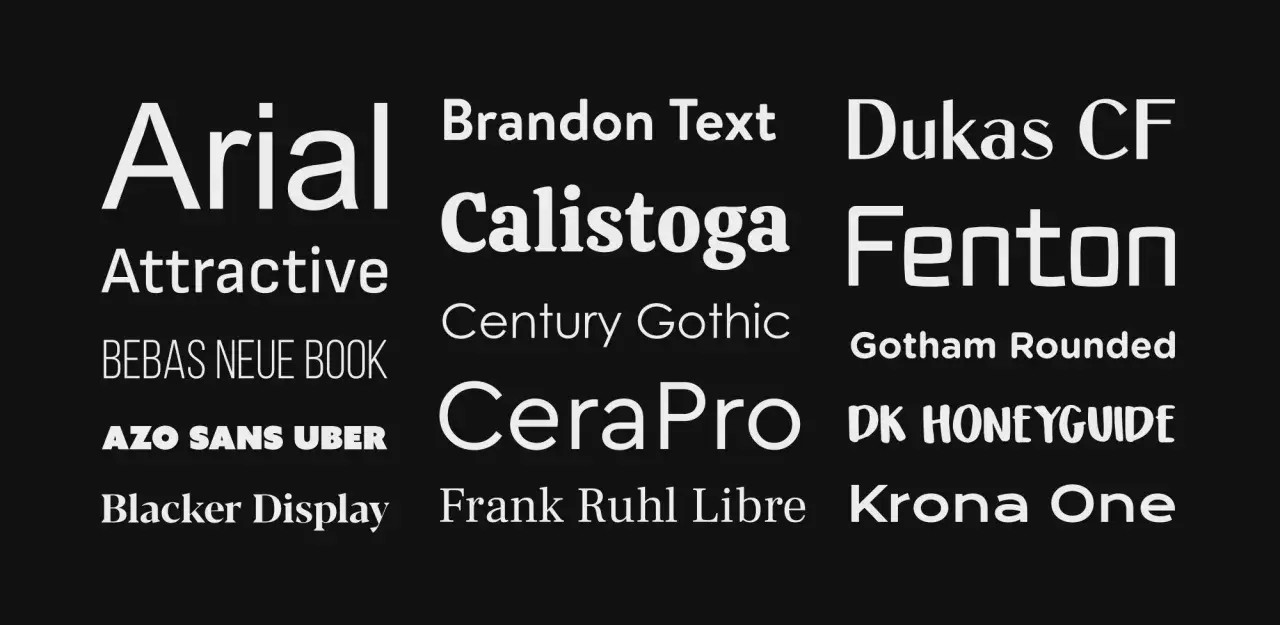
Czy krój liter w logo, plakacie albo książce to po prostu font? To zależy od tego, czy mówimy o wyglądzie znaków, czy o cyfrowym pliku, który pozwala ten wygląd wyświetlić i wydrukować. Wyjaśniam definicję fontu, różnicę między fontem, krojem pisma i czcionką, a także pokazuję, jak dobierać oraz poprawnie stosować fonty w projektach wizualnych.
Font łączy projekt liter z ich cyfrowym zastosowaniem
- Font to cyfrowy zapis zestawu znaków używany przez komputer, telefon lub program graficzny.
- Krój pisma opisuje wygląd liter, a font jest jego cyfrową realizacją.
- Czcionka w tradycyjnym znaczeniu była fizycznym elementem drukarskim, choć dziś słowo to bywa używane potocznie.
- Dobry wybór zależy przede wszystkim od czytelności, przeznaczenia i języka projektu.
Co dokładnie oznacza font
Najprościej mówiąc, font to cyfrowy zestaw znaków zapisany w formie, którą potrafi odczytać system operacyjny lub program. Zawiera nie tylko litery, lecz także cyfry, znaki interpunkcyjne, symbole i informacje potrzebne do prawidłowego rozmieszczenia ich w tekście.
Gdy instaluję font na komputerze, nie dodaję do systemu pojedynczego obrazka z alfabetem. Dodaję dane opisujące kształt znaków, ich proporcje, odstępy oraz sposób wyświetlania w różnych rozmiarach. Dzięki temu ten sam zapis może pojawić się na stronie internetowej, w katalogu, na plakacie albo w publikacji drukowanej.
W codziennej rozmowie słowo „font” często oznacza po prostu wygląd pisma. Technicznie precyzyjniej jest jednak powiedzieć, że font jest cyfrową realizacją określonego kroju pisma. To rozróżnienie nie zawsze ma znaczenie przy pracy w edytorze tekstu, ale przy projektowaniu, licencjonowaniu i przygotowaniu materiałów do druku staje się bardzo praktyczne.
Font, krój pisma i czcionka to nie to samo
Te trzy pojęcia są często mieszane, ponieważ w programach graficznych i rozmowach projektowych funkcjonują niemal zamiennie. Ja rozdzielam je w prosty sposób, patrząc na to, co jest projektem, co zapisem, a co fizycznym nośnikiem.
| Pojęcie | Znaczenie | Przykład |
|---|---|---|
| Krój pisma | Projekt i charakterystyczny wygląd całego zestawu znaków. | Helvetica, Garamond, Futura |
| Font | Cyfrowy zapis kroju pisma wraz z konkretnymi danymi i odmianami. | plik Garamond-Regular.otf |
| Czcionka | Tradycyjnie fizyczny element używany w składzie drukarskim. | metalowy klocek z literą |
Krój pisma można porównać do projektu mebla, a font do pliku technicznego, na podstawie którego ten mebel da się wykonać. Czcionka była natomiast konkretnym, materialnym elementem używanym przez drukarza. Współczesny język komputerowy spłaszczył te różnice, dlatego określenie „czcionka” jest dziś często potocznym odpowiednikiem słowa „font”.
Podobnie działa pojęcie rodziny fontów. Jedna rodzina może obejmować odmianę regularną, pogrubioną, kursywę, wersję półgrubą i wąską. Nie są to całkowicie przypadkowe warianty, lecz spójny system zaprojektowany do różnych funkcji, takich jak tekst główny, nagłówki czy wyróżnienia.
Jakie informacje zawiera cyfrowy font
Font przechowuje kształty znaków, nazywane glifami. Glif to konkretny graficzny wariant znaku, dlatego jedna litera może mieć kilka glifów, na przykład zwykłą formę, ozdobną alternatywę albo wersję używaną w ligaturze.
Znaki i obsługiwane języki
Przy polskich projektach szczególnie ważny jest zestaw znaków diakrytycznych. Font powinien zawierać między innymi ą, ć, ę, ł, ń, ó, ś, ź i ż. Brak tych znaków prowadzi do zastępowania ich innymi krojami, pustymi kwadratami albo literami bez ogonków, co natychmiast psuje spójność kompozycji.
Odstępy i układ tekstu
O jakości fontu decydują także dane dotyczące kerningu, czyli korekty odstępów między konkretnymi parami liter. Para „A” i „V” może wymagać innego ustawienia niż „H” i „I”. W krótkim napisie logo takie szczegóły są bardzo widoczne, choć w długim akapicie łatwo je przeoczyć.
Font może również zawierać informacje o wysokości liter, linii bazowej, interlinii oraz proporcjach znaków. To dlatego dwa fonty ustawione w tym samym rozmiarze, na przykład 12 punktów, mogą wyglądać na różnej wielkości i zajmować zupełnie inną ilość miejsca.
Format pliku
Do najczęściej spotykanych formatów należą TTF i OTF, wykorzystywane głównie w systemach operacyjnych oraz programach graficznych. W internecie stosuje się przede wszystkim WOFF i WOFF2, ponieważ zostały przygotowane z myślą o wydajnym ładowaniu fontów na stronach.
W starszych projektach można znaleźć format Type 1, ale nie powinien być pierwszym wyborem przy nowych realizacjach. Coraz większe znaczenie mają również fonty zmienne, które w jednym pliku mogą przechowywać płynne zakresy grubości, szerokości lub pochylenia. Dają projektantowi większą elastyczność, lecz nie każdy program i system obsługuje je w identyczny sposób.
Najważniejsze rodzaje fontów i ich zastosowanie
Podział fontów nie służy wyłącznie porządkowaniu katalogów. Każdy rodzaj niesie określone skojarzenia i inaczej zachowuje się w tekście. Przy wyborze zaczynam od funkcji projektu, a dopiero później zastanawiam się, czy dany krój jest modny albo efektowny.
Fonty szeryfowe
Fonty szeryfowe mają niewielkie zakończenia kresek, czyli szeryfy. Kojarzą się z tradycją, literaturą i drukiem, dlatego często dobrze sprawdzają się w książkach, esejach, albumach oraz tekstach o historycznym lub artystycznym charakterze.
Ich ozdobne zakończenia nie gwarantują automatycznie lepszej czytelności. Przy małym rozmiarze, słabym kontraście lub na ekranie o niskiej jakości mogą stać się zbyt drobne. Zwykle wybieram je tam, gdzie tekst ma mieć spokojny, bardziej redakcyjny charakter.
Fonty bezszeryfowe
Fonty bezszeryfowe, nazywane też groteskami, nie mają dodatkowych zakończeń kresek. Są prostsze wizualnie i często dobrze działają w interfejsach, podpisach, prezentacjach oraz materiałach przeznaczonych głównie do czytania na ekranie.
Nie oznacza to, że każdy bezszeryfowy font będzie dobry dla strony internetowej. Zbyt cienka odmiana może znikać na telefonie, a zbyt ciasne odstępy utrudnią czytanie. Liczy się konkretna konstrukcja znaków, nie sama etykieta kategorii.
Fonty odręczne i dekoracyjne
Fonty skryptowe naśladują pismo ręczne, kaligrafię lub lettering, a dekoracyjne mają silnie indywidualny charakter. Potrafią nadać plakatowi czy zaproszeniu wyjątkowy ton, jednak zwykle najlepiej używać ich w krótkich napisach, nie w wieloakapitowym tekście.
Najczęstszy błąd polega na stosowaniu ozdobnego fontu wszędzie, gdzie chcemy dodać projektowi charakteru. W praktyce wystarczy jeden wyraz lub nagłówek, a resztę dobrze oprzeć na spokojniejszym kroju. Dzięki temu akcent pozostaje czytelny i nie zamienia kompozycji w wizualny chaos.
Przeczytaj również: Ozdobniki tekstu w liternictwie - jak dekorować bez chaosu
Fonty monospacowane
W fontach monospacowanych każdy znak zajmuje taką samą szerokość. Kojarzą się z maszyną do pisania, kodem i estetyką techniczną, dlatego mogą pasować do plakatów inspirowanych komputerami, archiwami lub drukiem.
W zwykłym tekście zajmują jednak więcej miejsca niż kroje proporcjonalne. Używam ich głównie jako świadomego środka stylistycznego albo wtedy, gdy równa szerokość znaków ma praktyczne znaczenie.
Jak wybrać font do projektu wizualnego
Dobór fontu zaczynam od odpowiedzi na trzy pytania. Co ma zostać przeczytane, gdzie tekst będzie oglądany i jakie emocje ma wywołać? Innego rozwiązania potrzebuje etykieta małego opakowania, innego plakat oglądany z kilku metrów, a jeszcze innego długi artykuł na ekranie.
- Do długiego tekstu wybieram krój o wyraźnych różnicach między znakami i wygodnym rytmie słów.
- Do nagłówka mogę użyć mocniejszego kontrastu, większej grubości lub bardziej charakterystycznych proporcji.
- Do interfejsu sprawdzam czytelność małych liter, cyfr oraz podobnych znaków, takich jak „I”, „l” i „1”.
- Do projektu artystycznego dopuszczam większą ekspresję, ale pilnuję, aby ozdobność nie odebrała tekstowi funkcji.
Przy polskich materiałach sprawdzam próbkę zawierającą cały zestaw znaków diakrytycznych, cyfry i podstawowe symbole. Testuję też kilka rzeczywistych zdań, ponieważ font może wyglądać świetnie w pokazowym słowie, a źle w dłuższym akapicie.
Nie zaczynam od instalowania kilkunastu fontów. Najczęściej wystarczą dwie rodziny: jedna do tekstu i druga do nagłówków, choć czasem jeden dobrze zaprojektowany krój z kilkoma odmianami daje jeszcze lepszy efekt. Nadmiar fontów rozprasza uwagę i utrudnia utrzymanie hierarchii.
Typowe błędy związane z używaniem fontów
Jednym z częstszych problemów jest sztuczne pogrubianie lub pochylanie tekstu, gdy font nie ma prawdziwej odmiany bold albo italic. Program tylko deformuje znaki, przez co tracą proporcje i wyglądają mniej profesjonalnie. Lepiej użyć właściwego wariantu z rodziny.
Drugi błąd to ignorowanie licencji. Font darmowy nie zawsze oznacza font przeznaczony do zastosowań komercyjnych. Przed użyciem w logo, reklamie, produkcie lub publikacji sprawdzam, czy licencja obejmuje konkretny sposób wykorzystania i czy nie wymaga dodatkowej opłaty.
Problemy pojawiają się również przy przesyłaniu projektu do innej osoby. Jeśli program nie ma dostępu do użytego fontu, może zastąpić go innym. W druku pomaga osadzenie fontów w pliku PDF, a w projektach logo często zamienia się tekst na krzywe, choć wtedy późniejsza edycja liter staje się trudniejsza.
Unikam też oceniania kroju wyłącznie po nazwie lub podglądzie alfabetu. Najlepszy test to konkretny materiał, właściwy rozmiar, odpowiedni kontrast i docelowe medium. Font, który wygląda znakomicie na dużym ekranie, może okazać się nieczytelny na etykiecie albo w przypisie książki.
Font jako narzędzie budowania charakteru obrazu
Litery są częścią kompozycji tak samo jak kolor, linia i faktura. Ten sam napis może wyglądać klasycznie, surowo, dziecięco albo technologicznie zależnie od użytego kroju, jego skali, odstępów i miejsca na płaszczyźnie.
Dlatego definicję fontu najlepiej zapamiętać w dwóch warstwach. W sensie technicznym jest to cyfrowy zapis znaków, a w praktyce projektowej narzędzie, które wpływa na rytm, czytelność i emocjonalny odbiór całej pracy.
Kiedy rozumiem różnicę między krojem pisma a fontem, łatwiej mi świadomie podejmować decyzje. Nie wybieram już „ładnych literek” z listy, tylko dopasowuję system znaków do materiału, odbiorcy i warunków, w których projekt będzie oglądany.